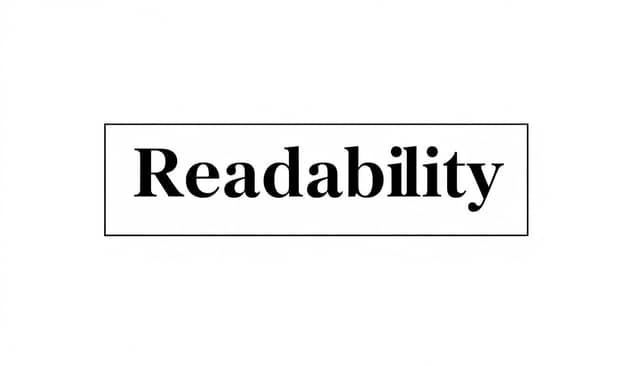
Hey, ich verstehe dich—Tippfehler in der Typografie können deine Designs unprofessionell und schwer lesbar erscheinen lassen. Wenn du jemals frustriert warst von nicht passenden Schriftarten oder unordentlichem Abstand, bist du nicht allein. Glücklicherweise wirst du, wenn du dranbleibst, einfache Tipps entdecken, um häufige Fehler zu vermeiden und deinen Text scharf und sauber aussehen zu lassen.
Les weiter, und du wirst lernen, wie du die richtigen Schriftarten auswählst, eine klare visuelle Hierarchie erstellst und Details wie Abstand und Ausrichtung anpasst. Diese einfachen Tricks helfen deinem Text, ohne viel Aufhebens oder Verwirrung herauszustechen.
Lass uns mit den Grundlagen beginnen, damit deine Typografie von Anfang bis Ende poliert und einladend aussieht.
Wichtige Erkenntnisse
- Begrenze deine Schriftarten auf 2-3, um dein Design sauber zu halten und Verwirrung zu vermeiden. Zu viele Schriftarten lassen deinen Inhalt überladen wirken.
- Kombiniere Schriftarten, die gut kontrastieren, wie Serifenschriften mit Sans-Serifenschriften, um deinen Text visuell ansprechend und klar zu gestalten.
- Erstelle eine starke visuelle Hierarchie, indem du unterschiedliche Schriftgrößen und -stärken verwendest, damit die Leser verstehen, was am wichtigsten ist.
- Richte den Text links aus, um das Lesen zu erleichtern; zentrierte oder blockjustierte Texte können stilvoll sein, aber die Lesbarkeit auf einigen Bildschirmen verringern.
- Passe den Abstand zwischen Buchstaben und Zeilen an, um zu verhindern, dass der Text überladen oder zu locker wirkt, was das Folgen erleichtert.
- Verwende hohen Kontrast zwischen Text und Hintergrund—dunkel auf hell oder umgekehrt—um sicherzustellen, dass dein Text auf einen Blick lesbar ist.
- Wähle Schriftarten, die mehrere Sprachen und Formate unterstützen, um deinen Inhalt vielseitig und bereit für zukünftiges Wachstum zu halten.
- Vermeide „Witwen“, „Waisen“ und „Flüsse“, indem du Probleme mit dem Textfluss behebst, was hilft, deinen Inhalt ordentlich und leicht lesbar zu halten.
- Halte die Konsistenz bei Aufzählungen, Listen und Hervorhebungen, um deinen Inhalt organisiert und professionell aussehen zu lassen.
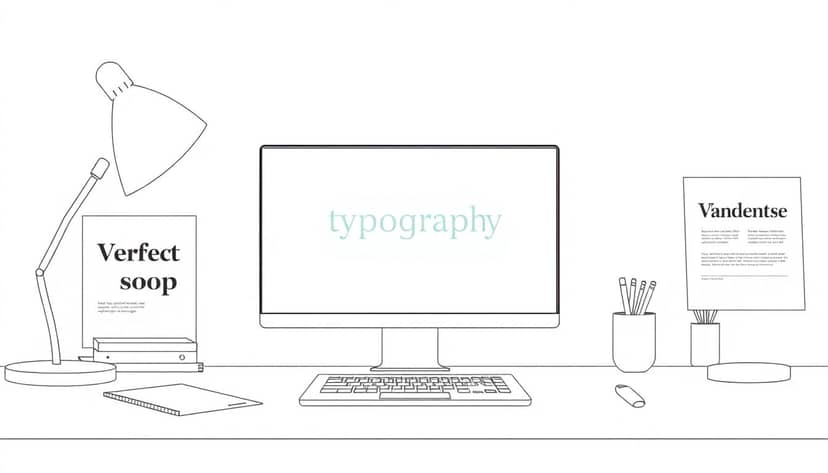
Das Vermeiden häufiger typografischer Fehler kann einen großen Unterschied darin machen, wie dein Inhalt wahrgenommen wird und wie leicht er zu lesen ist. Hier ist ein schneller, unkomplizierter Leitfaden, um dir zu helfen, diese Probleme zu erkennen und zu beheben, bevor sie die Leser abschrecken.
1. Begrenze die Anzahl der verwendeten Schriftarten
Zu viele Schriftarten auf einer Seite schaffen Chaos und lenken die Leser ab. Wenn du dich auf 2-3 Schriftarten beschränkst, bleibt dein Design sauber und professionell. Zum Beispiel könntest du eine für Überschriften und eine andere für Fließtext verwenden, aber vermeide es, für jeden Abschnitt eine neue Schriftart zu wählen. Studien zeigen, dass schlechte Typografie, einschließlich übermäßiger Schriftarten, dazu führt, dass 38% der Menschen aufhören, sich mit einer Website zu beschäftigen [Quelle](https://automateed.com/why-is-grammarly-so-expensive-an-in-depth-analysis/).
2. Schriftarten sorgfältig kombinieren
Bei der Auswahl von Schriftarten, die zusammenpassen, ist der Kontrast entscheidend. Kombiniere eine Serifenschrift (wie Times New Roman) mit einer Sans-Serifenschrift (wie Arial) für Klarheit und visuelles Interesse. Stelle sicher, dass die Schriftarten sich ergänzen und nicht miteinander kollidieren. Wenn du unsicher bist, suche nach Schriftkombinationen, die von Experten empfohlen werden, wie zum Beispiel die auf [beste Schriftarten für Buchcover](https://automateed.com/best-fonts-for-book-covers/).
3. Eine klare Hierarchie erstellen
Führe die Leser durch deinen Inhalt mit typografischer Hierarchie. Verwende größere, fettere Schriftarten für Überschriften, etwas kleinere für Unterüberschriften und eine angenehme Größe für den Fließtext. Dies hilft, Verwirrung zu vermeiden und die Seite organisiert zu halten. Wenn die Hierarchie klar ist, wissen die Leser, was sie zuerst lesen sollen und was am wichtigsten ist.
4. Die richtige Textausrichtung für Lesbarkeit verwenden
Links ausgerichteter Text ist am einfachsten zu lesen, besonders bei längeren Inhalten. Zentrierter oder blockjustierter Text kann elegant aussehen, könnte aber zu ungleichmäßigen Abständen führen, was das Folgen erschwert. Konsistente Ausrichtung schafft ein ordentliches, professionelles Erscheinungsbild und verbessert die Lesbarkeit auf verschiedenen Geräten.
5. Den Buchstabenabstand (Kerning und Tracking) anpassen
Zu nah beieinander oder zu weit auseinander, können Buchstaben das Lesen erschweren. Passe das Kerning (den Abstand zwischen bestimmten Buchstabenkombinationen) an, um ungeschickte Lücken zu beheben, und stelle das Tracking (den Gesamtabstand zwischen Buchstaben) ein, um den Fluss zu verbessern. Zum Beispiel kann eine leichte Erhöhung des Trackings in Überschriften den Text hervorheben, ohne überladen zu wirken.
Schaffe eine klare Hierarchie mit Schriftgröße und -gewicht, richte den Text richtig aus und verwende angemessenen Zeilenabstand. Hoher Kontrast zwischen Text und Hintergrund trägt ebenfalls zur Lesbarkeit bei.
Die richtige Ausrichtung verbessert die Struktur und den Fluss deines Textes, was es den Lesern erleichtert, deinen Inhalt zu scannen und zu verstehen. Konsistente Ausrichtung erhöht die allgemeine visuelle Konsistenz.